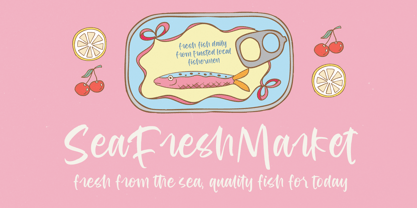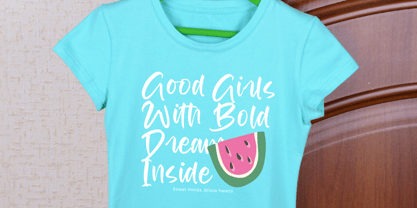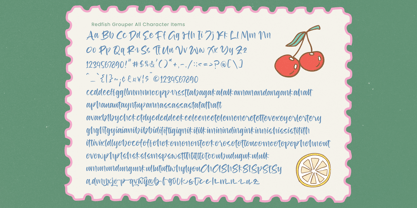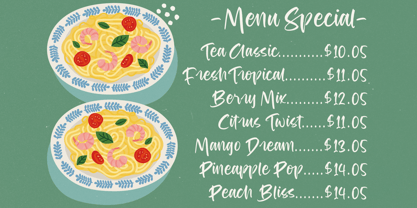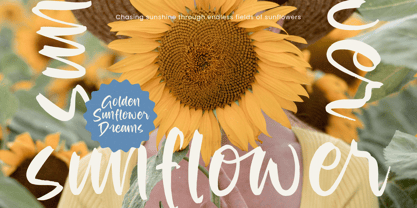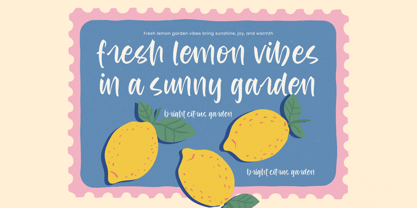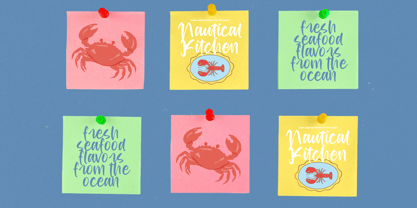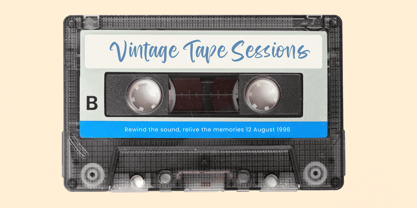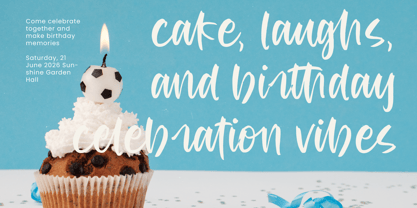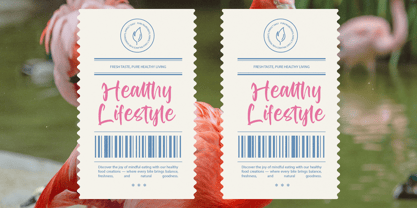
Redfish Grouper
Die Schriftfamilie Redfish Grouper wurde von Heru Utama Putra entworfen und von Stylishtype Studio veröffentlicht. Redfish Grouper enthält 2 Stile und Familienpaketoptionen. Mehr über diese Familie
Redfish Grouper is a bold modern handwritten font with a quirky, playful character and soft organic strokes that feel lively and expressive. Dibuat untuk proyek yang butuh sentuhan cute, handmade, dan eye-catching, font ini tampil kuat dalam packaging, kids branding, food labels, logos, poster fun, hingga visual craft. Dengan 159 ligatures, 29 alternates, dan 2 style variations, Redfish Grouper memberi kamu fleksibilitas penuh untuk menciptakan lettering yang unik, casual, dan penuh personality.